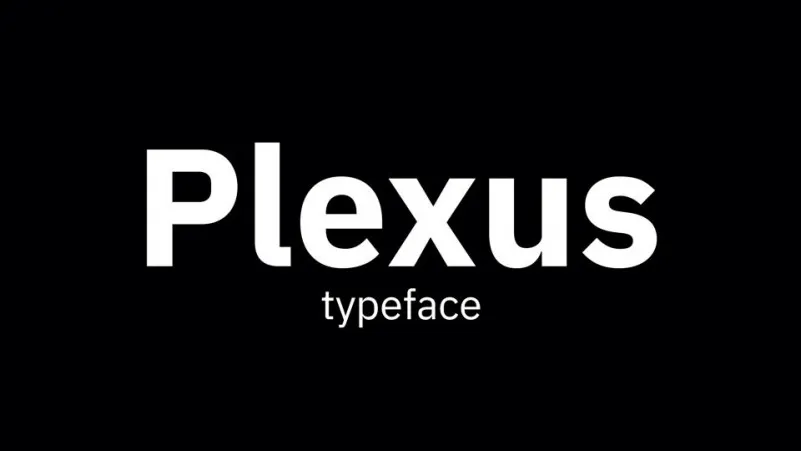
A Plexus Font Family é uma elegante família de letras gerais derivada do IBM Plex, apresentando um aspecto robusto caracterizado pela simplicidade e clareza típica dos sans serif. Ainda assim, o designer Joshua Smith decidiu neutralizar algumas das mais únicas características marcantes da IBM Plex que definem seu charme distintivo, criando uma combinação perfeita de modernidade e sofisticação. A família contém sete tipografias diferentes desde fina até grossa, garantindo um alcance visual consistente. Além disso, inclui um conjunto completo de caracteres, que vai dos alfabetos maiúsculo e minúsculo às letras numéricas e símbolos, bem como suporte para vários idiomas. Como tal, a Plexus Font Family é uma escolha ótima tanto para aplicativos digitais quanto para mídias impressas, proporcionando o necessário equilíbrio entre modernidade e legibilidade.